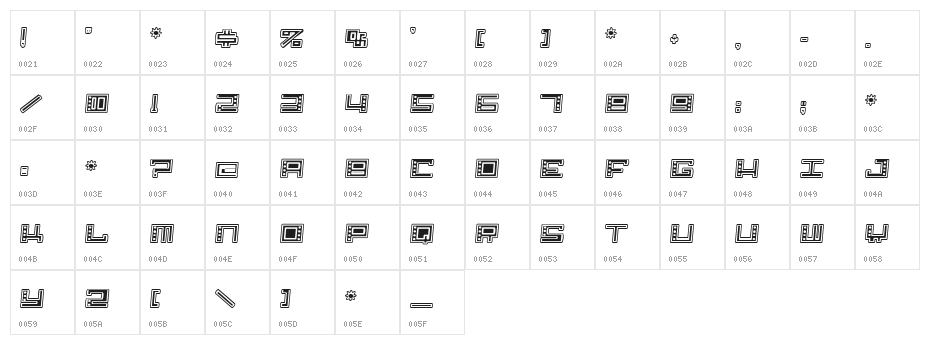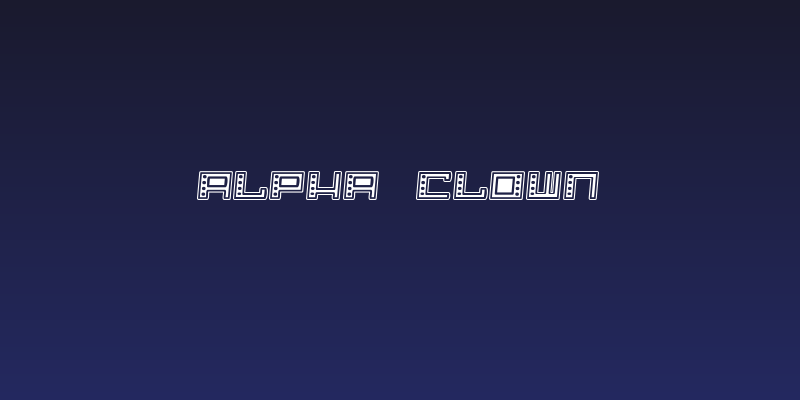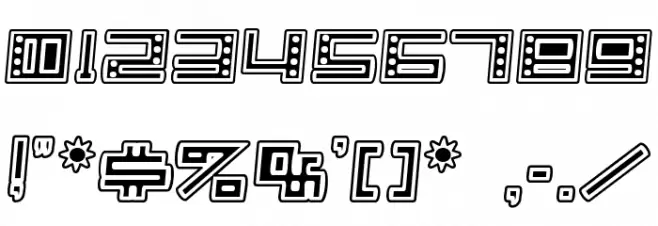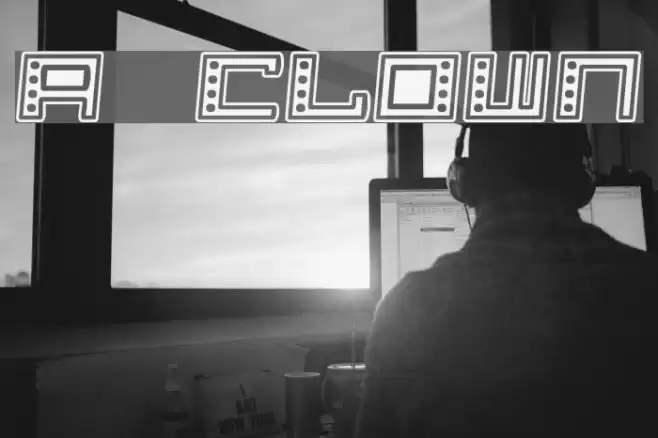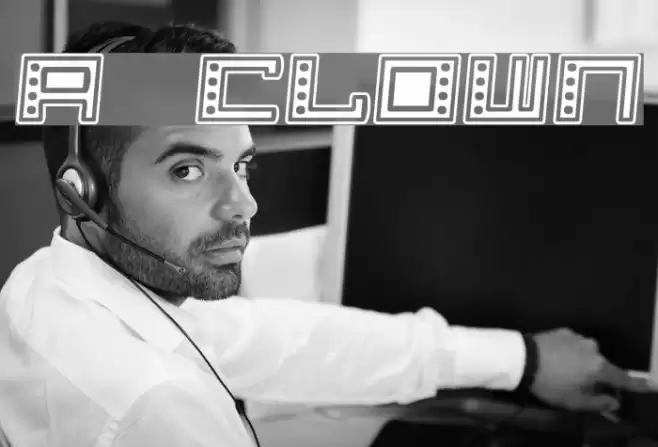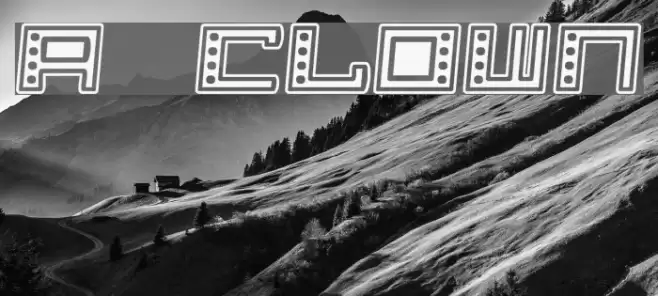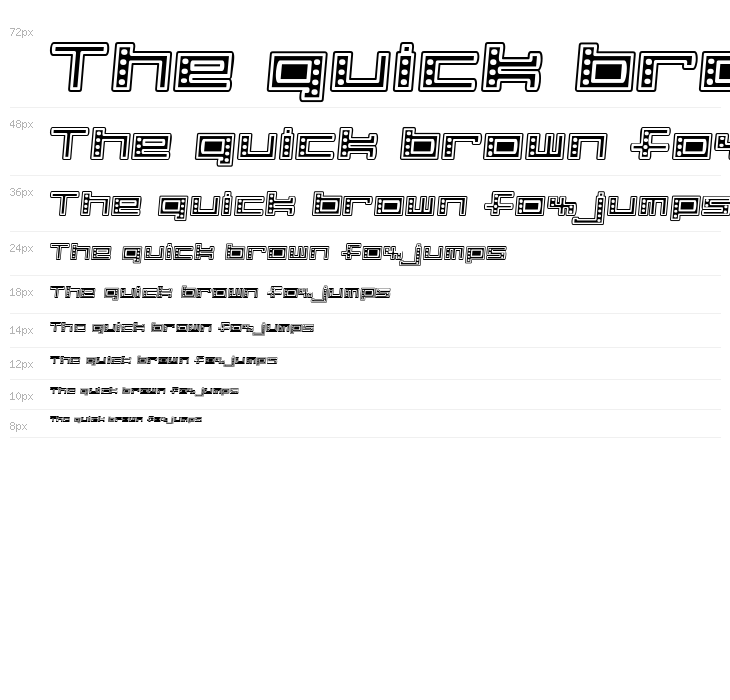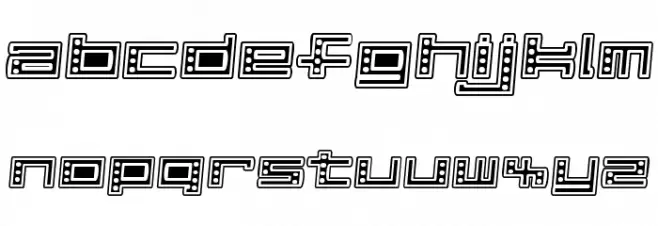
Alpha CLOWN Font
| Vorgeschlagene Projekte | Ideal for circus-themed posters, children's party invitations, playful branding, and festive event signage. |